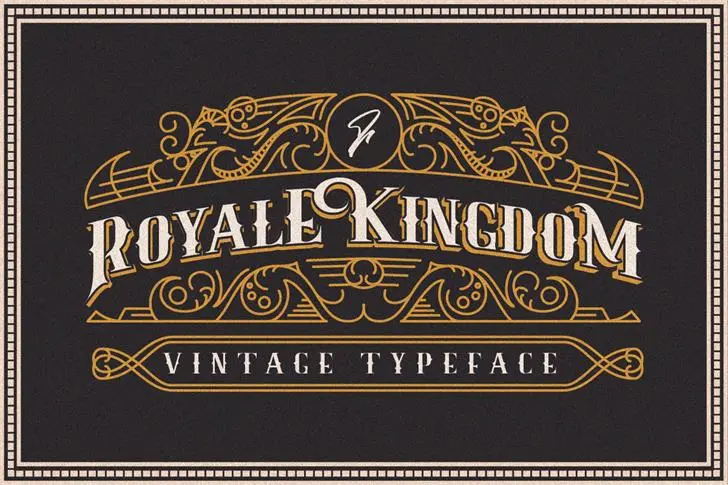
Royale Kingdom Typeface – Download Grátis
Introduzimos Royale. Fathialghazi é quem concebeu e compartilhou esta fonte tipo Royale Kingdom Typeface. É um estilo Vintage, perfeito para diversas aplicações. A sua forma antiquada faz os teus designs ganharem vida com uma ornamentação vintage que dura eternamente. Embora seja vintage, está disponível para uso em vários tipos de projectos, como Logotipos, Branding, Papéis de Correspondência, Design de T-Shirts, Cartões e muito mais. É a escolha ideal para dar um toque único aos teus projetos gráficos modernos ou tradicionais. Descubra agora Royale Kingdom Typeface e transforme as tuas criações em algo que se destaca!